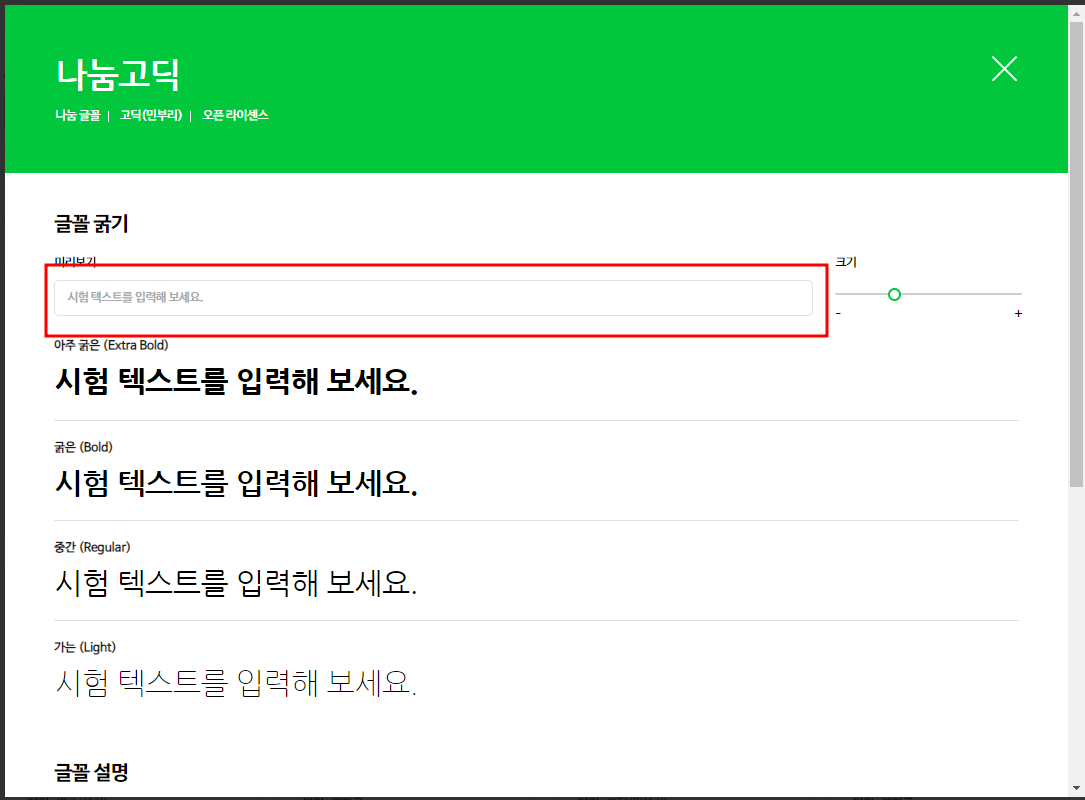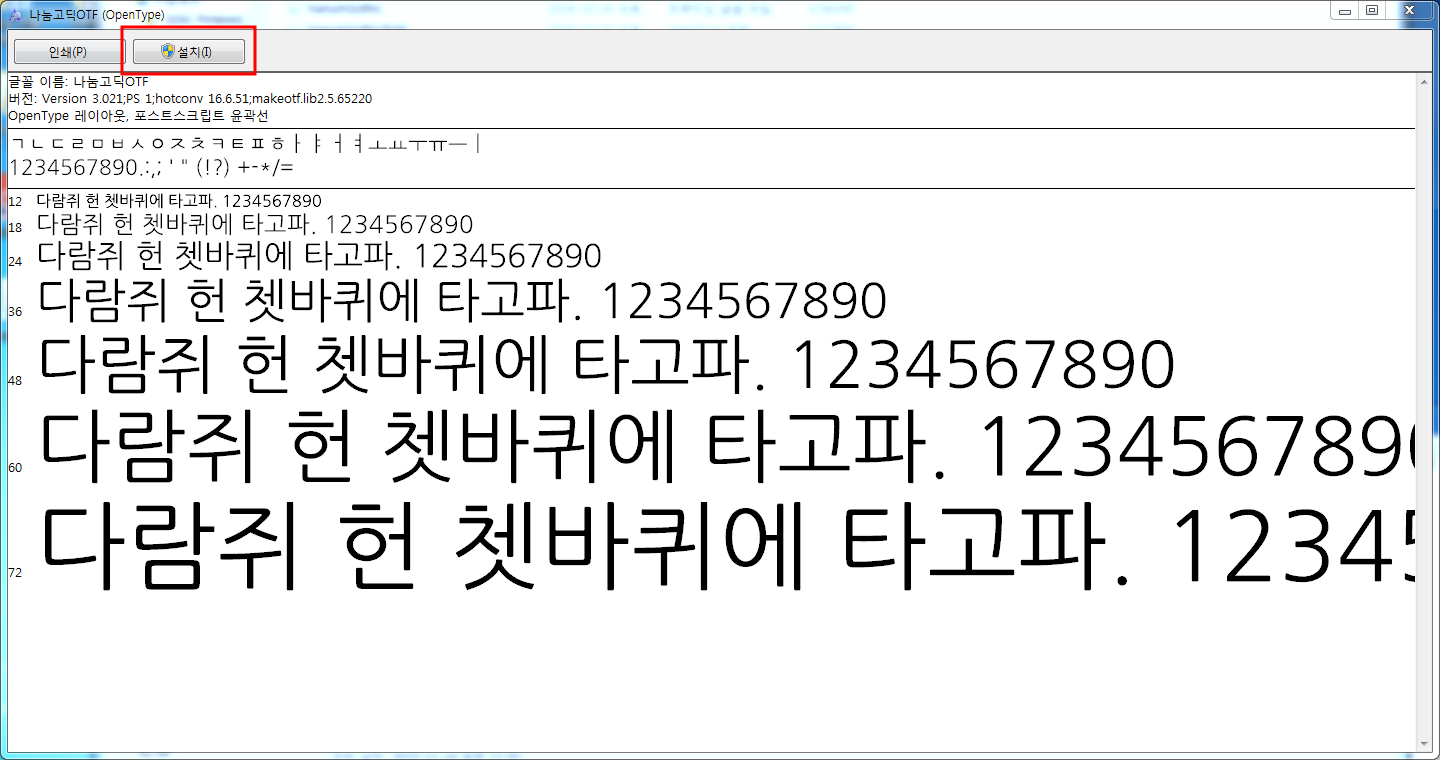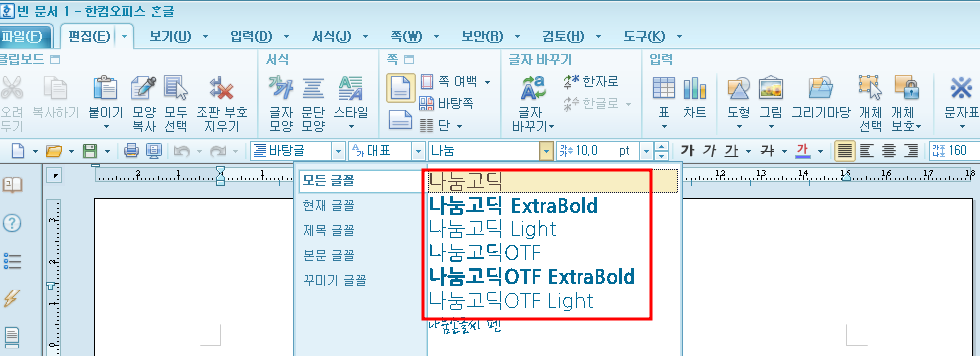
나눔고딕은 상업적으로도 사용이 가능하고 글자체가 친근하고 부드러워 보고서나 발표자료에 정말 많이 사용하고 있는 폰트입니다. 여러분은 이 나눔 글꼴을 네이버에서 제작한 사실을 아셨나요? 네이버에서 개인 및 기업 사용자를 포함한 모든 사용자에서 무료로 제공하고 있어 우리는 저작권 걱정 없이 마음 편히 사용할 수 있습니다. 자 그럼 직장인의 필수 글자체인 나눔고딕 폰트 다운로드와 설치 방법에 대하여 알아보도록 하겠습니다.